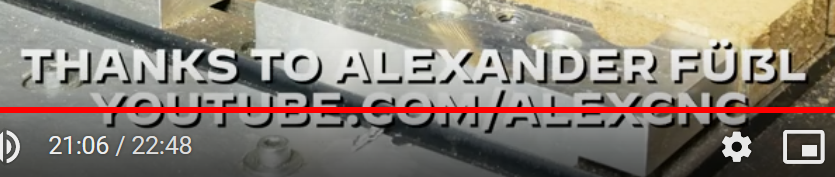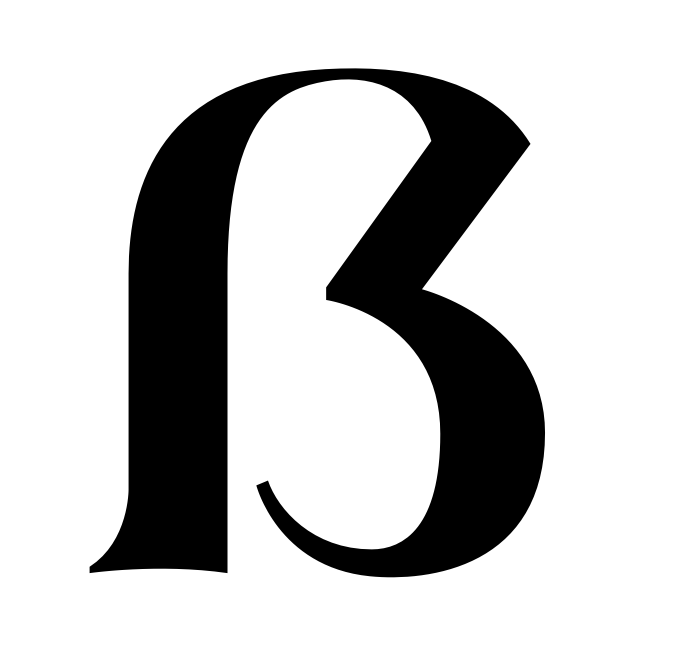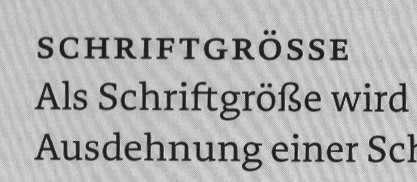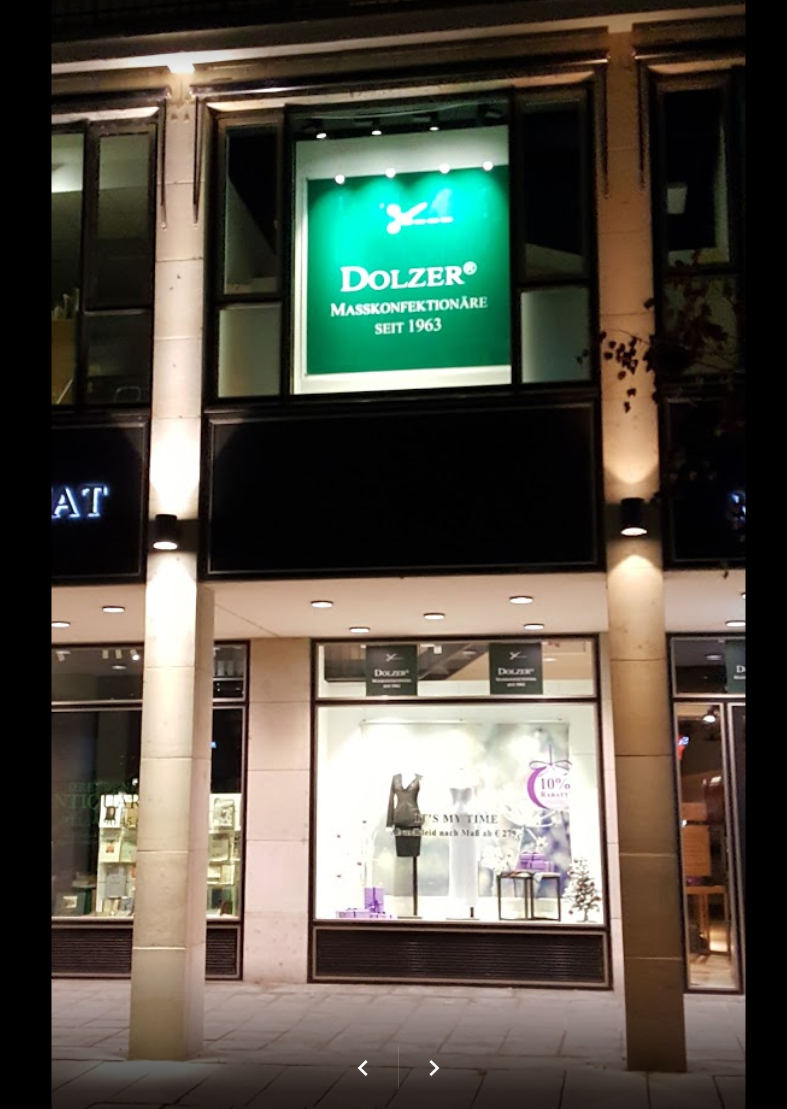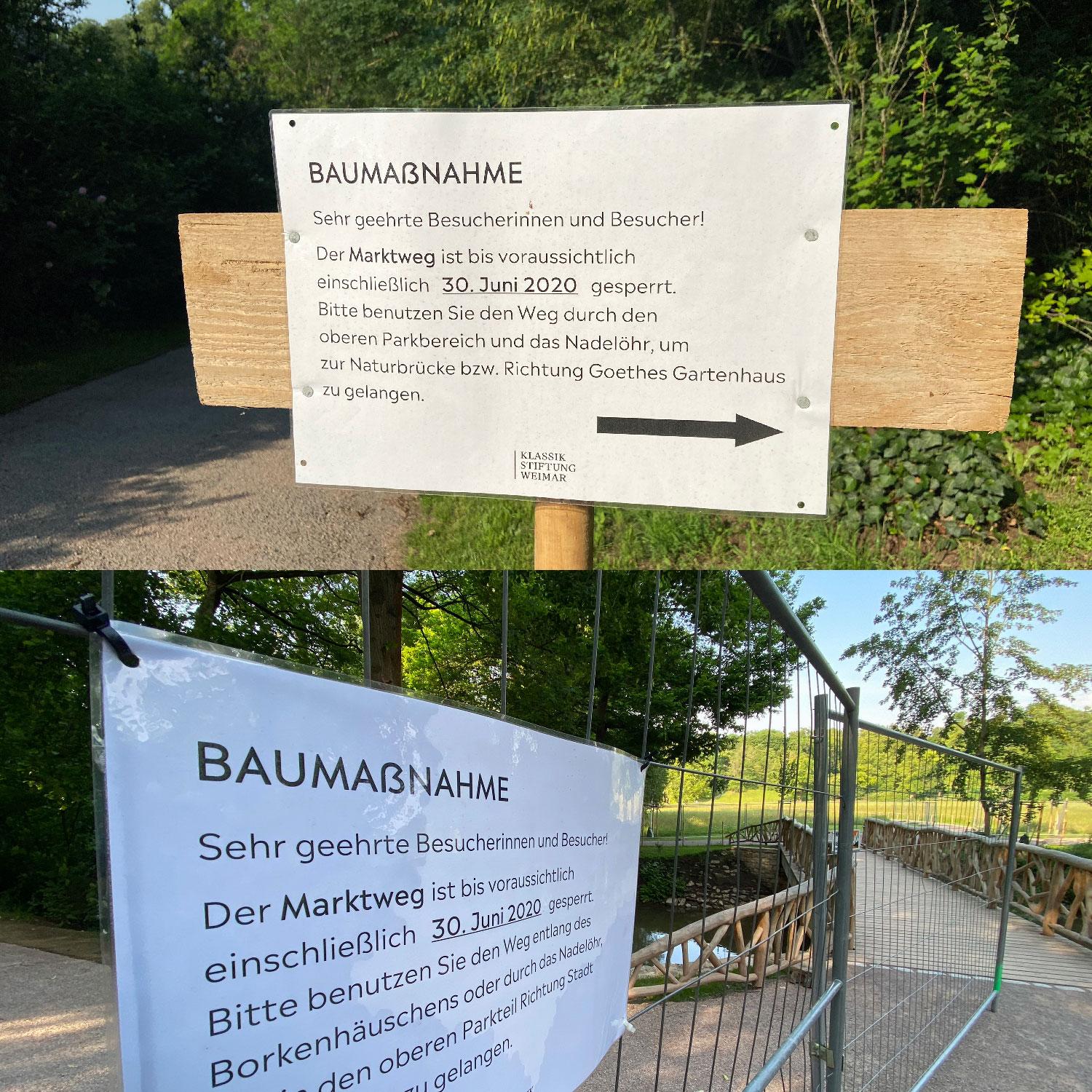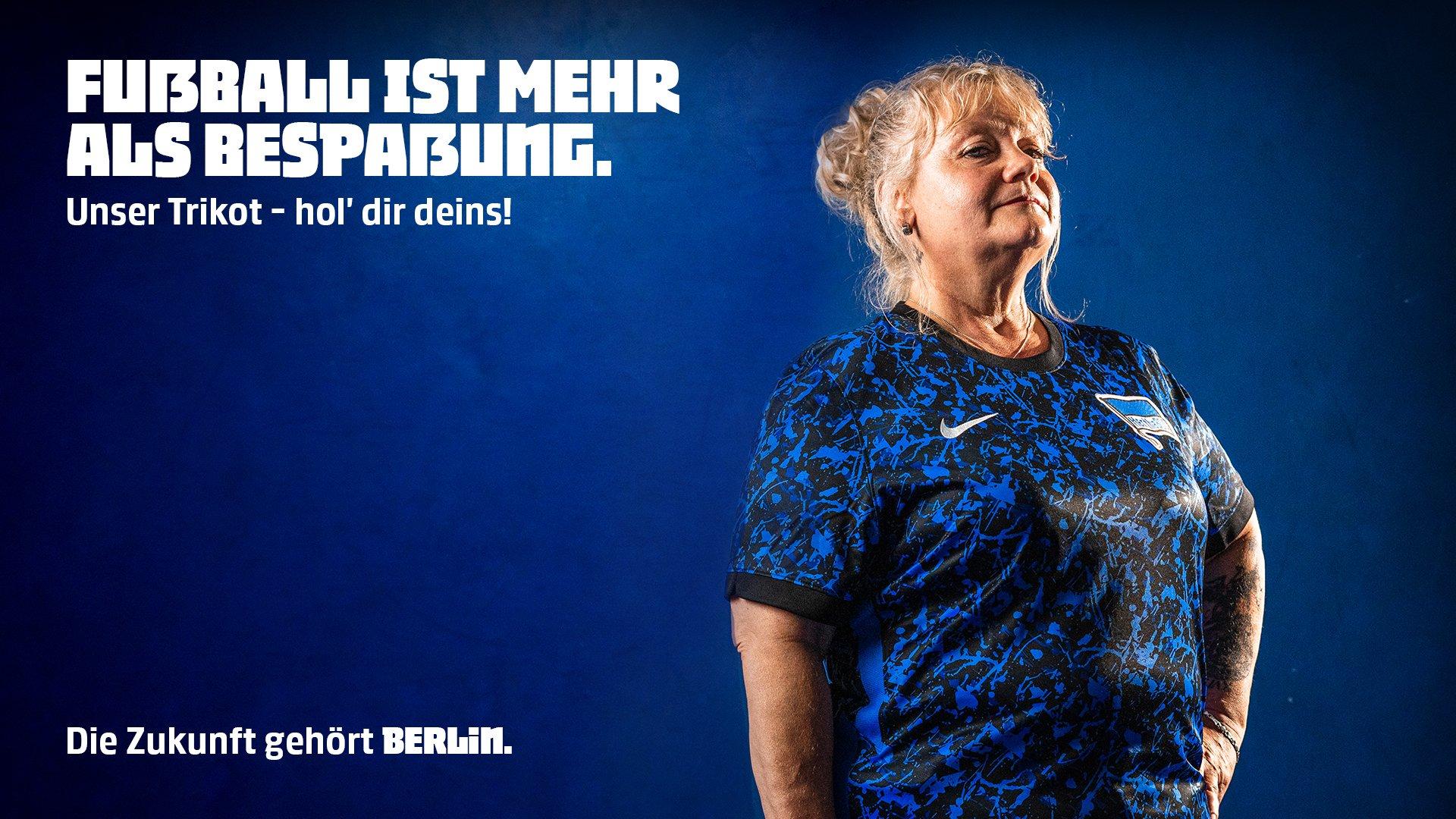
Ich liebe das große ẞ.
Ich finde es sinvoll da ich einmal vor einem Schild mit der Aufschrift "MASSKONFEKTUR" stand.
Für mich damals noch verwirrrend.
Ich finde es toll, dass das Zeichen jetzt im Unicode vorhanden ist.
Ich spreche das ẞ anders aus als das SS beziehungsweise den vokal davor.
Wenn man sich generell darauf einigt, dass alles in Versalien geschrieben werden kann,
denke ich es sollte hier auch die Möglichkeit geben unsere gesprochene Sprache schriftlich wiederzugeben.
Ich will mich nicht in die Regeln und Ursprünge (Ligatur) verstricken, da ich kein Experte bin, aber
ich finde Sprache sollte sich weiterentwickeln dürfen.
Trotzdem kann ich jeden verstehen der sagt er möchte gerne bei der alten Regelung bleiben (SS).
Es gibt ja auch dafür gute Gründe und Jeder soll nach seiner Façon selig werden.
Meine Stimme hat das große ẞ!
PS: Hier ist meins.
Neulich wurde hier »Das ABC der Typografie« vorgestellt. Da bin ich doch gleich auf Seite 46 darüber gestolpert:
Und in der Tat: Die Edit Serif hat kein Versal-Eszett. Schade.
Gesehen in Weimar:
Na, wenn das schon nicht im Epizentrum des VE klappen sollte, wo dann … :-?:hammer::ilovetype:
In Dresden war es damals, dass ich das Schild gesehen habe.
Aber kann sein, dass dort nicht MASSKONFEKTUR sondern eher MASSKONFEKTIONÄRE stand.
Das Eszett passt nicht schlecht zur Schrift, auch wenn es sogar für meinen Geschmack  (!) etwas zu weit geraten ist. Aber was soll das fürchterlich übergroße S?
Interessant, dass Du das schreibst – ist mir hier gar nicht aufgefallen, wahrscheinlich vor allem, weil kein Loch durch einen übergroßen Binnenraum ins Wortbild gerissen wird?
Ich bin eher daran hängengeblieben, dass man das N auch horizontal spiegeln könnte und es für die Lesbarkeit wahrscheinlich keinen Unterschied macht.
Im Nachhinein muss ich CatharsisFonts und R::bert recht geben, dass das ẞ eigentlich zu breit wäre, wenn die Buchstaben nicht so aneinandergemauert wären.